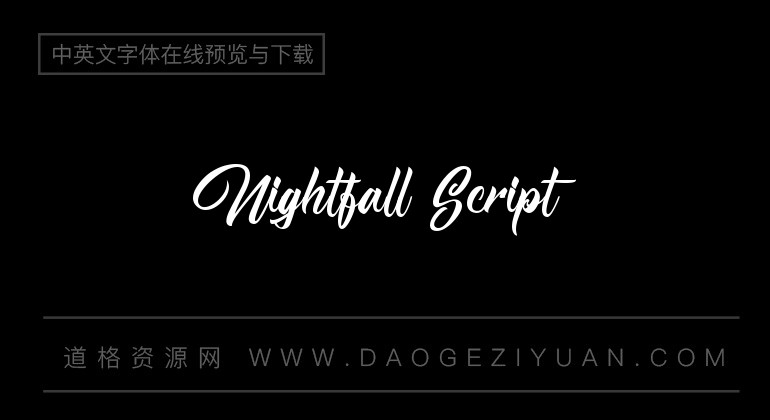
Nightfall Script
Nightfall Script 是一款新颖的手写体字体,它的特点是笔画细腻,笔划轻柔,给人一种温暖的感觉。它的字形设计灵活多变,可以用于各种不同的印刷项目,比如海报、书籍封面、标签、婚礼邀请函、商业广告等。它的文字特征精致,可以提升设计作品的美感,更能突出文字的魅力。
Nightfall Script是一款非常不错的手写艺术字体,具有很好的视觉感,适合于文化类的宣传设计、商业类品牌的广告和产品包装设计以及个性化文字排版等较多场景。